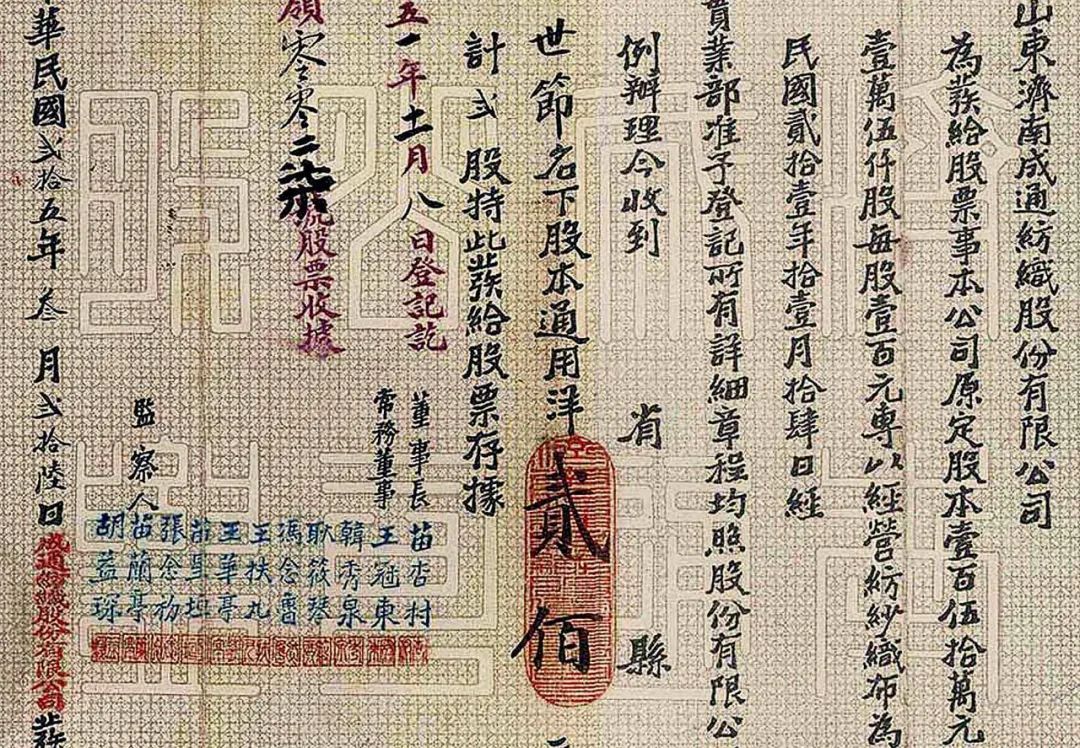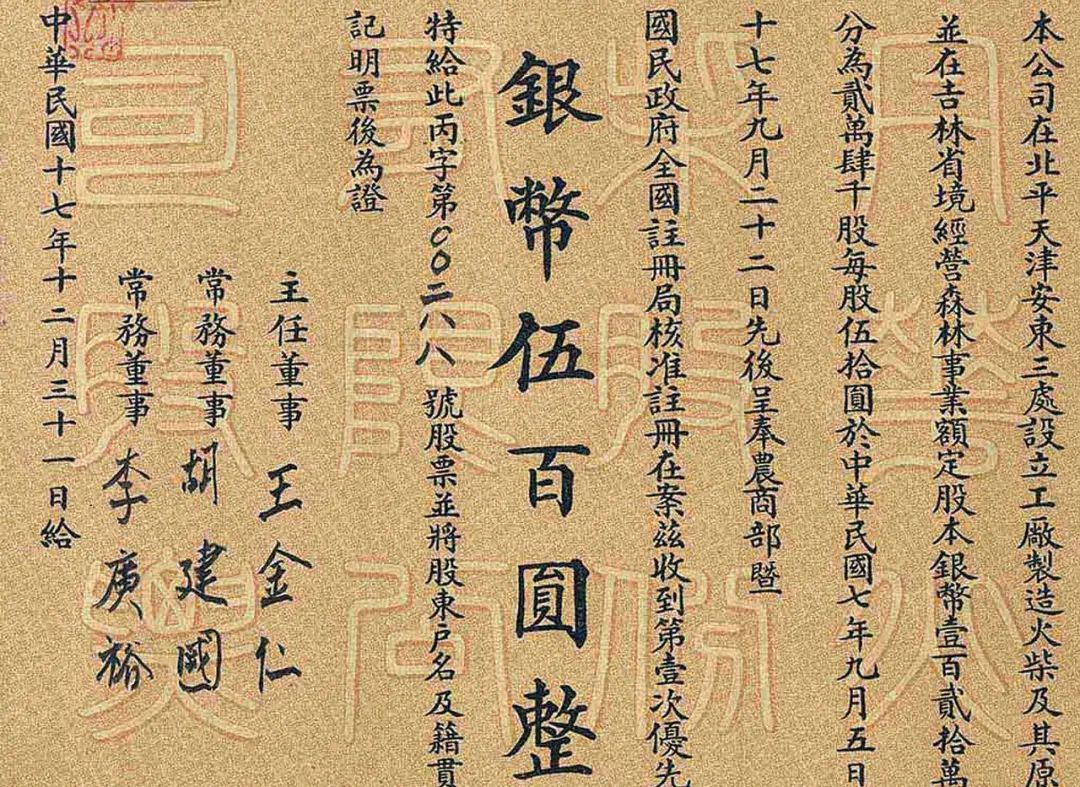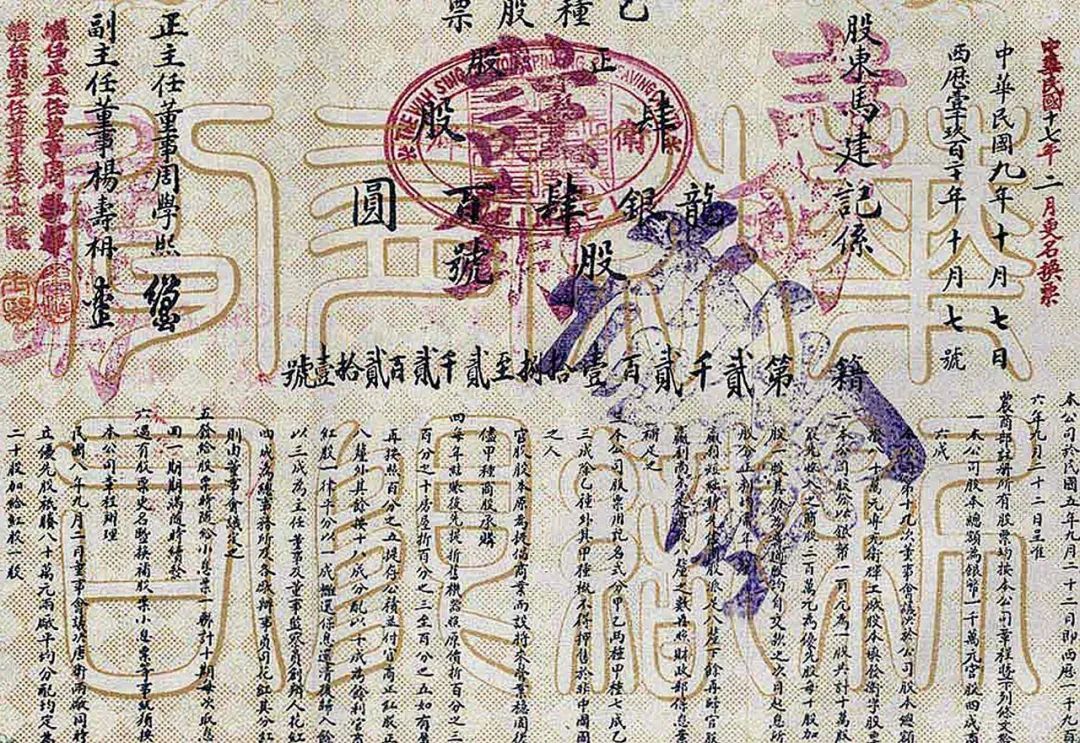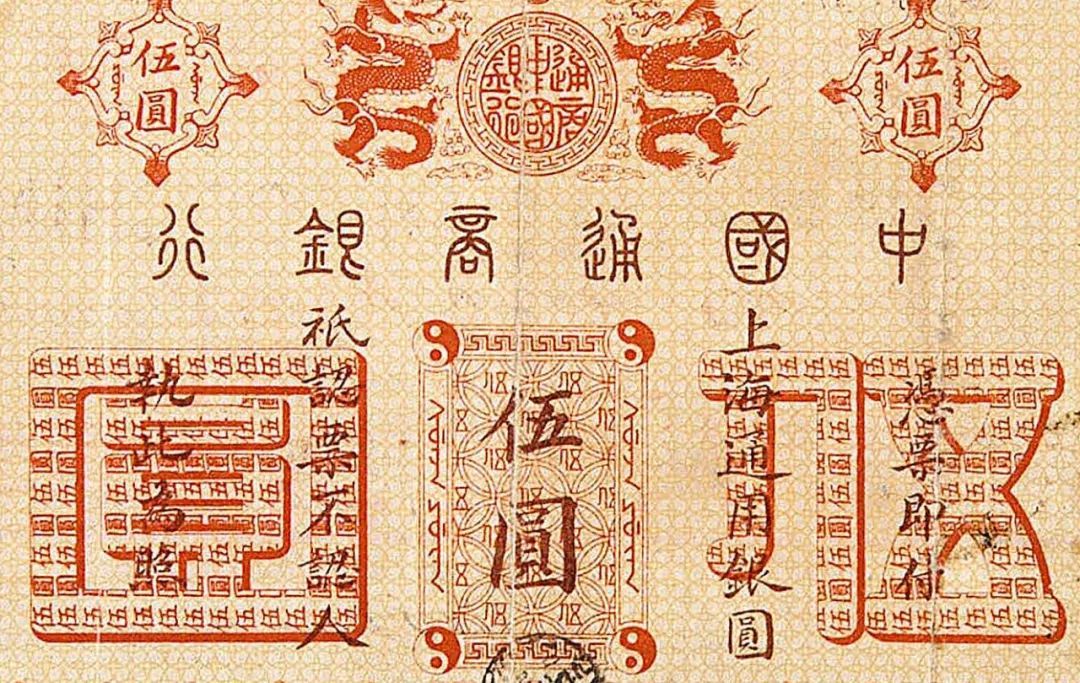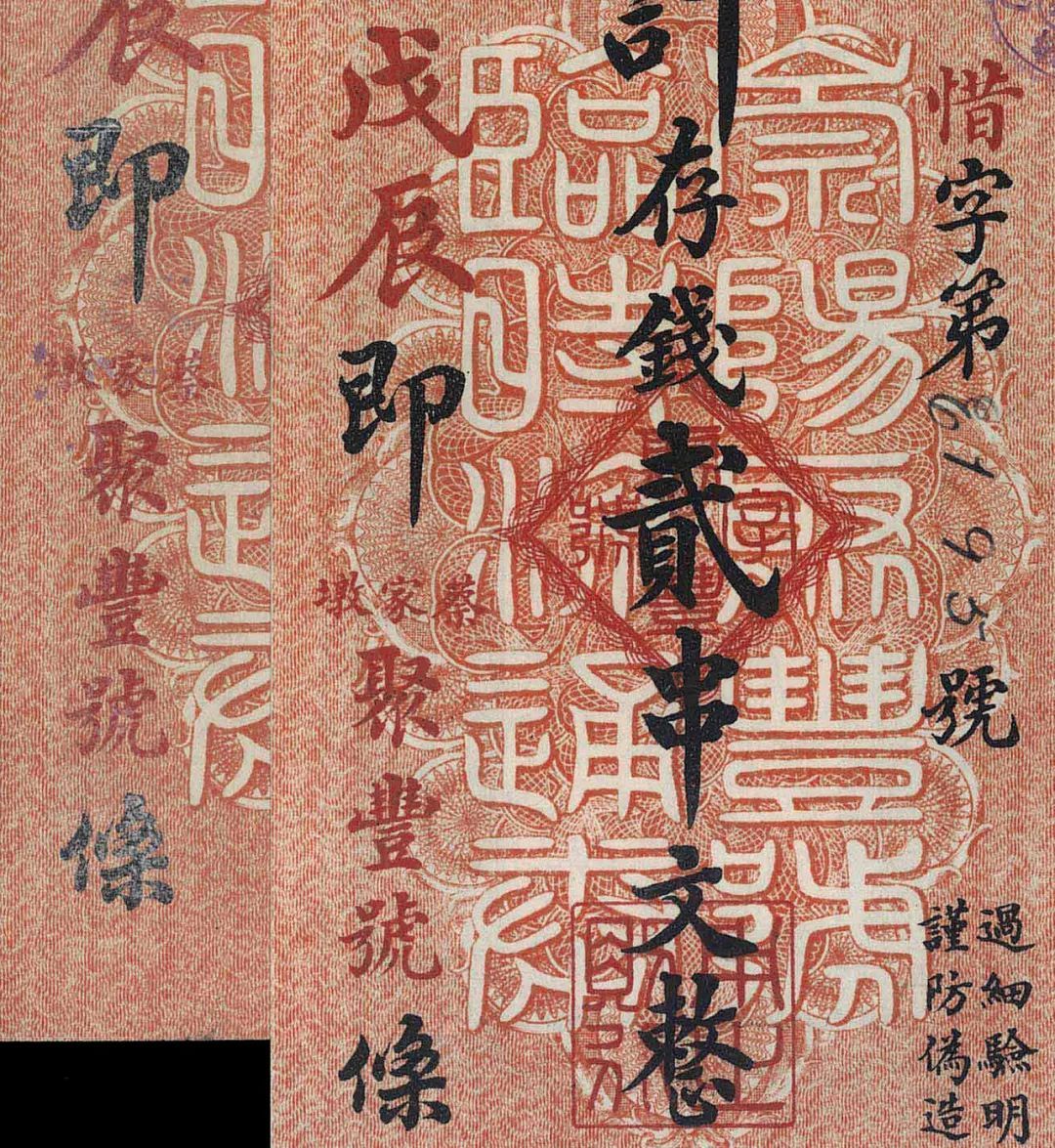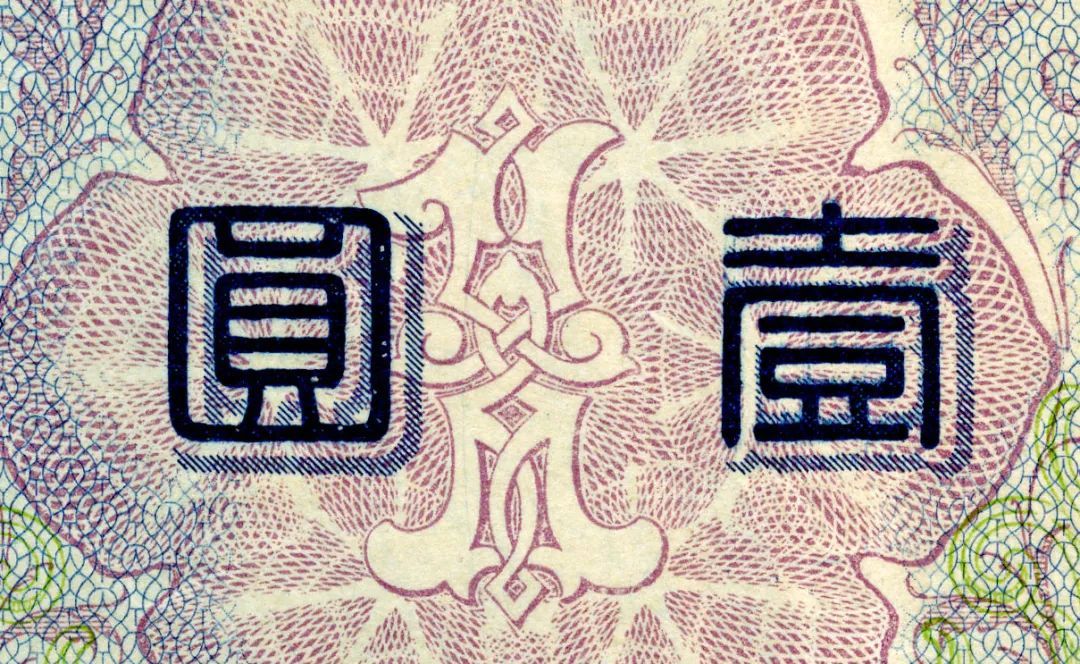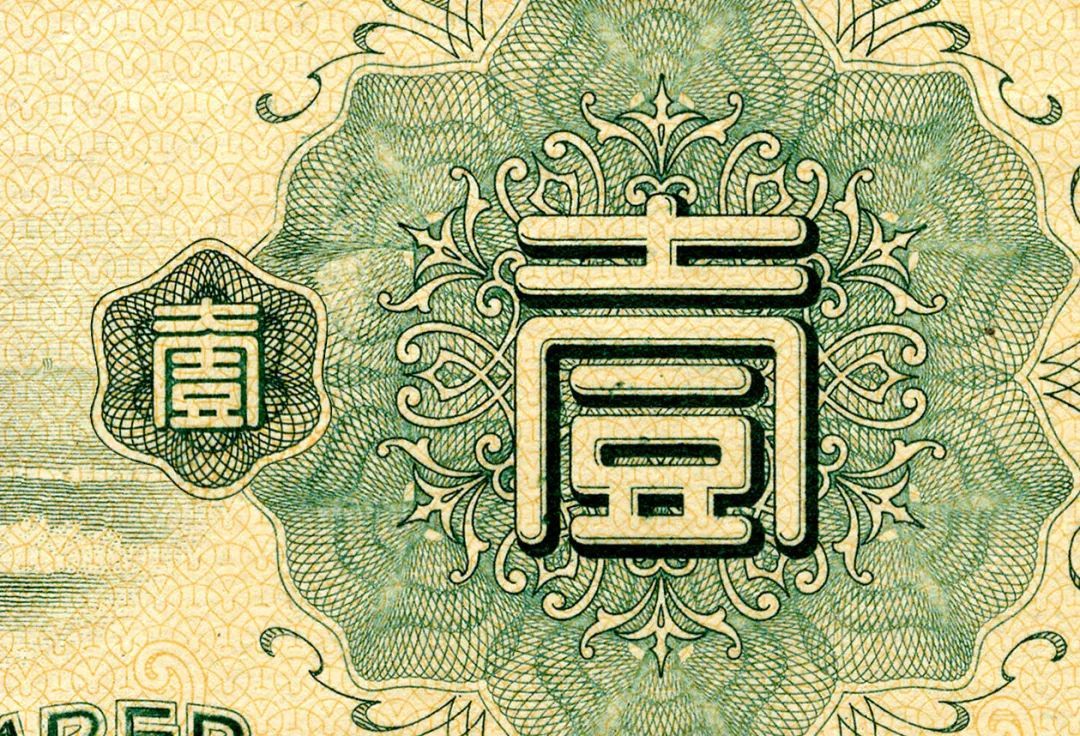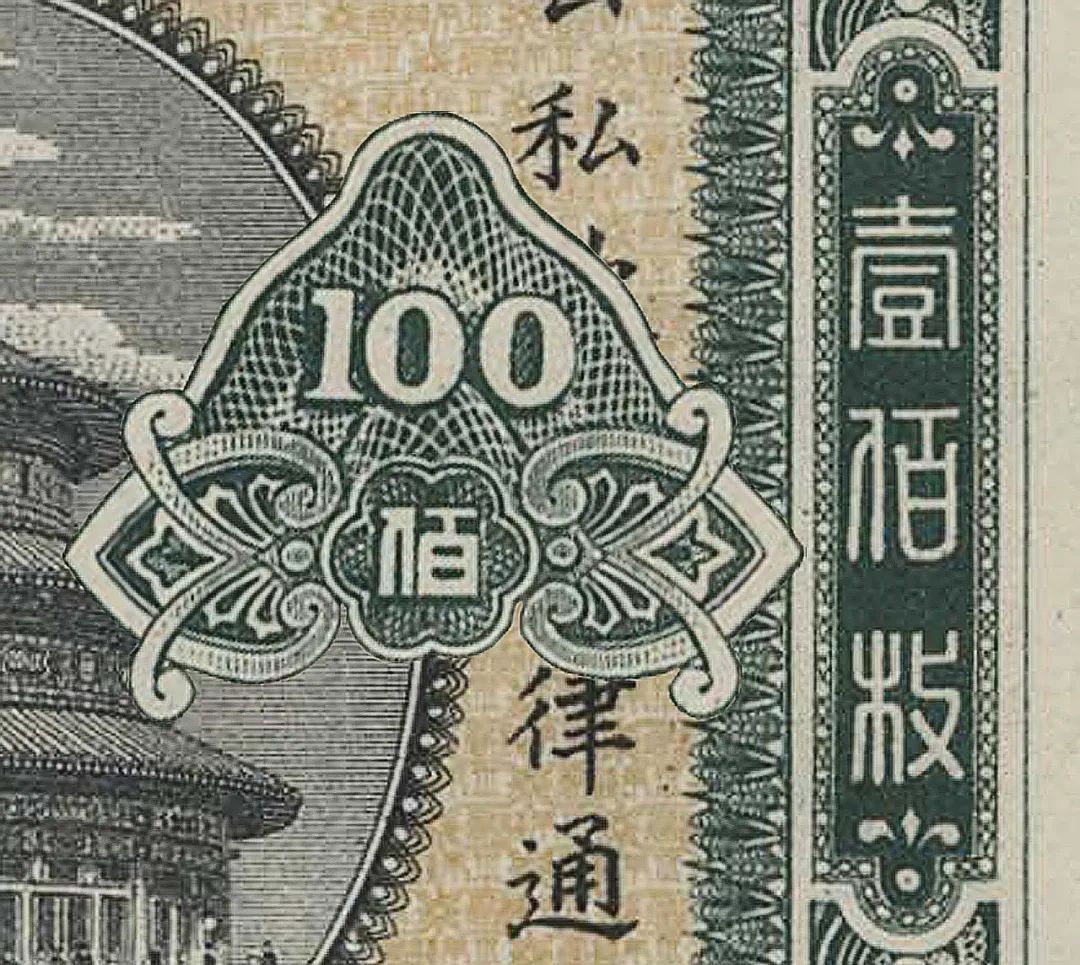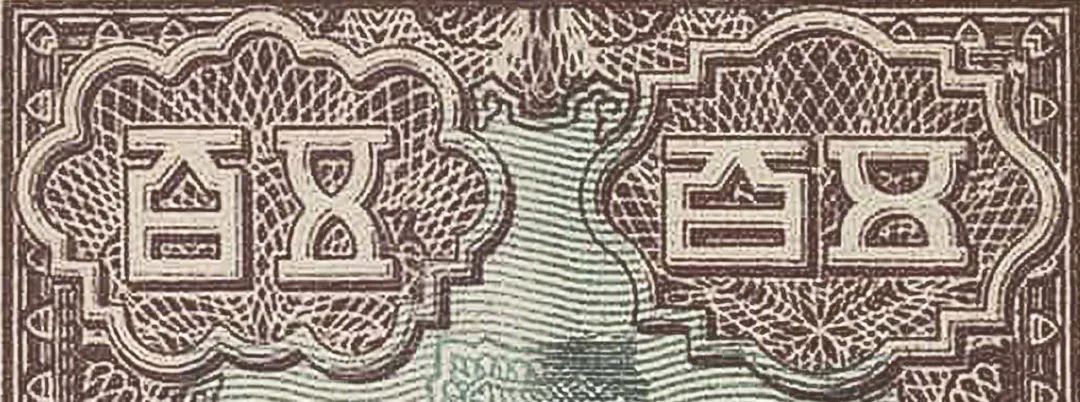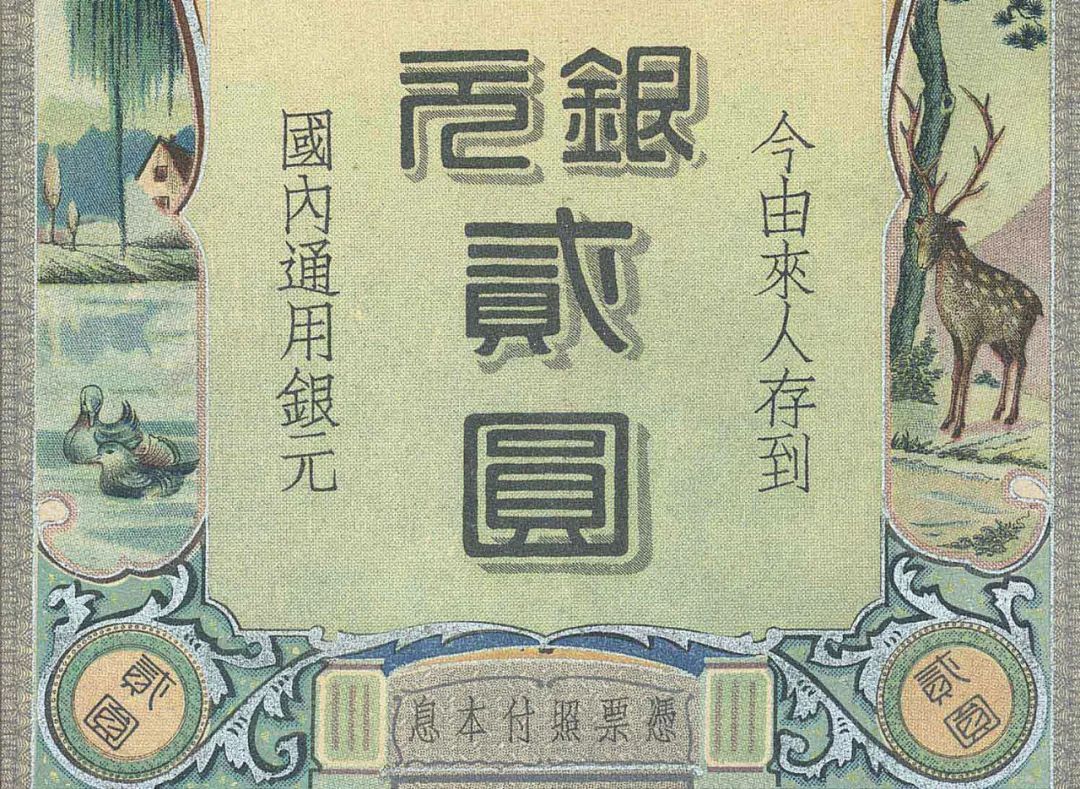
* * 美 術 篆 體 字 * *
從清代開始有了很多從西方引人的金融幣券的設計方式,圖案丶字體是中式的,版式設計採用西洋的,早期金融幣券中有一類字體比較流行,那就篆體字,包括日本的金融幣券上也愛用篆書體,小篆在古代一般會在比較正式的物件上會使用,可能是篆體字比較有裝飾味道吧!
以下圖片均來自網路 早期美術類的篆書體主要有如上四種設計樣式,雖然基礎造型是一樣的,但是有些會加一些裝飾,我們來看看:❶空心;❷空心、陰影;❸空心、襯邊、陰影;❹實心、虛線陰影。
- 股 票 -
- 紙 幣 -
- 其 他 -
▲ 偽滿州時期的郵票上全是篆書美術字組合
▲ 現在的日本郵票上的「日本郵便」還是採用篆書美術字
▲ 現在的日本護照封面也是篆書美術字